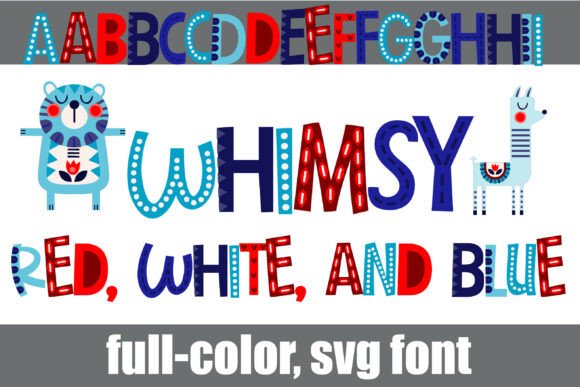
Whimsy Red, White, and Blue
Die richtigen Designelemente zu finden, kann eine Herausforderung sein, aber Whimsy Red, White, and Blue bietet eine außergewöhnliche Sammlung, die Ihre Arbeit sofort aufwertet.
Egal, ob Sie POD-Produkte (Print on Demand), Hochzeitseinladungen oder Social-Media-Grafiken erstellen, Whimsy Red, White, and Blue ist die ideale Wahl.